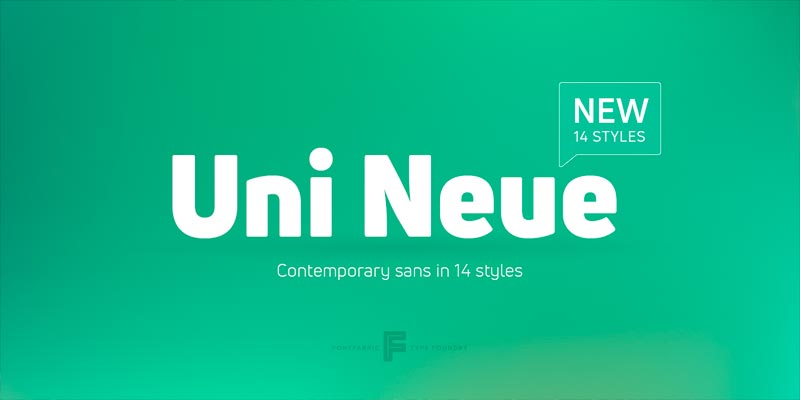
Font Uni Neue
Zakupiliśmy nowoczesną rodzinę fontów Uni Neue, składającą się z 14 odmian. Font z jednej strony ma geometryczny charakter, co nadaje mu profesjonalnego wyglądu, z drugiej strony litery są mocno zaokrąglone, co sprawia przyjazne wrażenie.